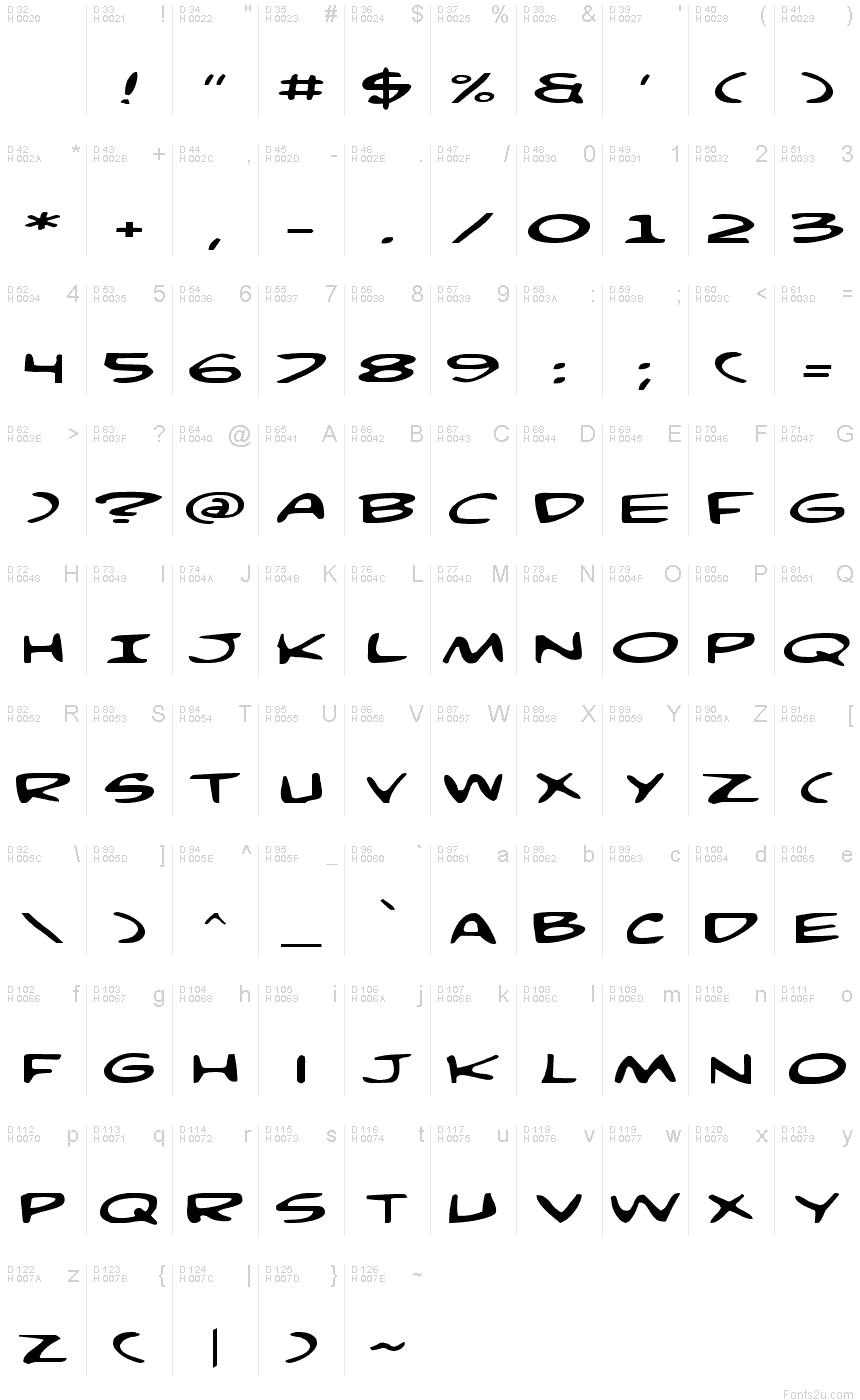
Comic Book Commando Exp
Comic Book Commando Exp od Iconian Fonts to darmowy komiksowy krój pisma, który oddaje szybki, przerysowany styl ręcznie rysowanych napisów akcji. Szerokie łuki, ściśnięte wnętrza liter i lekko nierówna linia nadają mu energię „efektu dźwiękowego”, przypominającą tytuł na okładce klasycznego komiksu o superbohaterach lub dynamiczny kadr pełen akcji.
Comic Book Commando Exp świetnie sprawdza się na okładkach komiksów, plakatach w stylu arcade, miniaturach na YouTube, gadżetach dla dzieci, ulotkach eventowych, projektach naklejek i wyrazistej grafice do mediów społecznościowych. Ten darmowy font najlepiej prezentuje się w większym rozmiarze, gdzie jego rozciągnięty rytm i zabawny charakter mogą w pełni wybrzmieć; w mniejszych tekstach dla zachowania równowagi warto łączyć go z prostym krojem bezszeryfowym.